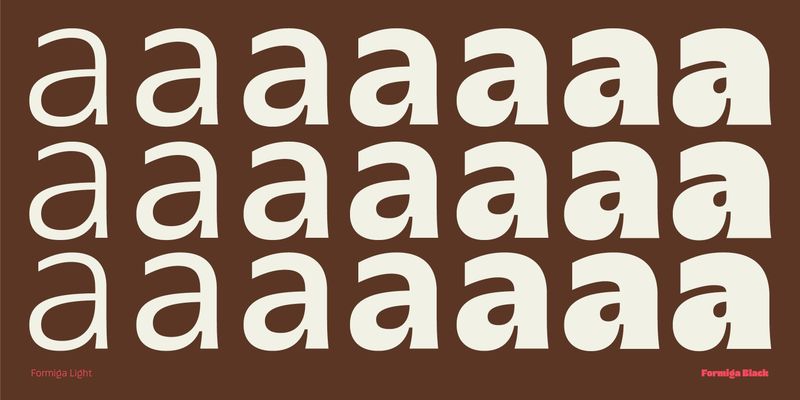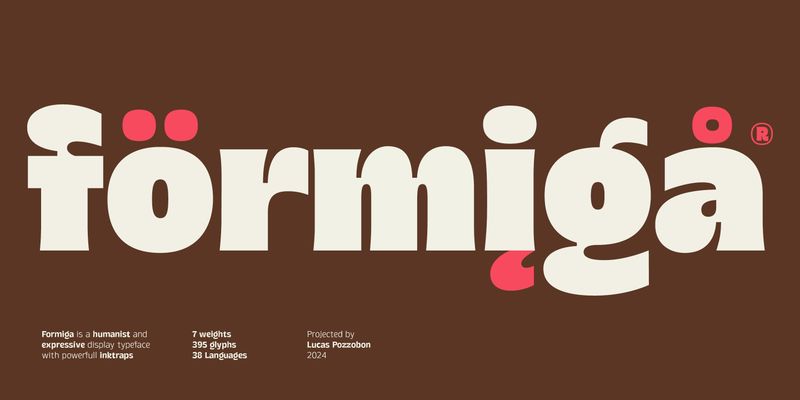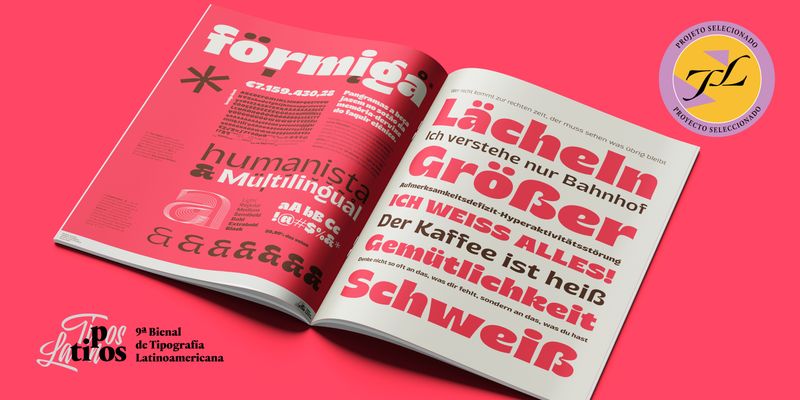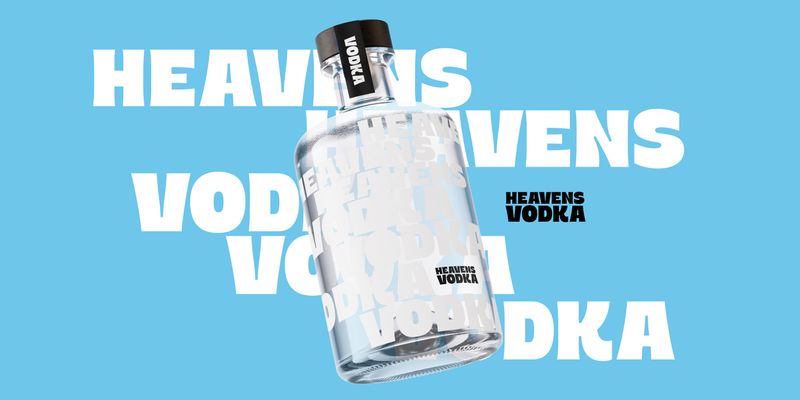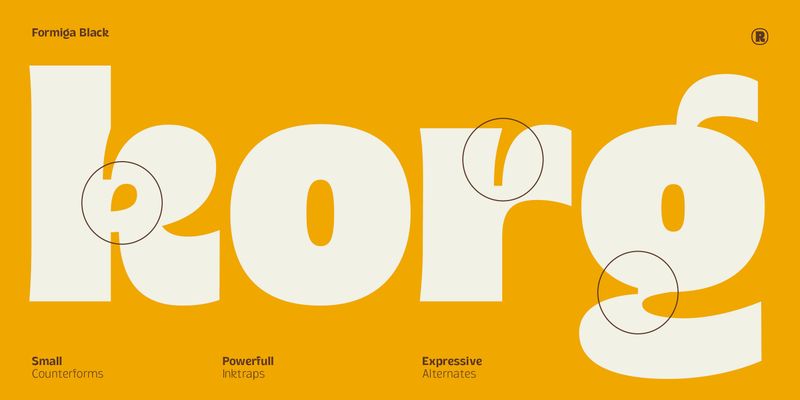
„Formiga“ ist eine ausdrucksstarke, humanistische Akzidenzschrift, die sich hervorragend für ausdrucksstarke Überschriften in modernen, zeitgemäßen Designkontexten sowie für Verpackungen mit einem frischen, kühnen und kraftvollen Stil eignet. Die Schriftfamilie ist in sieben Schriftstärken, von Light bis Black, erhältlich. Sie unterstützt 38 Sprachen und enthält OpenType-Features zur Verbesserung der Lesbarkeit bestimmter Zeichen.